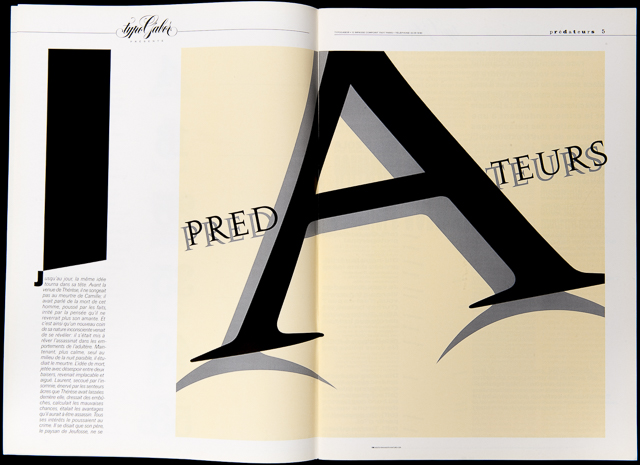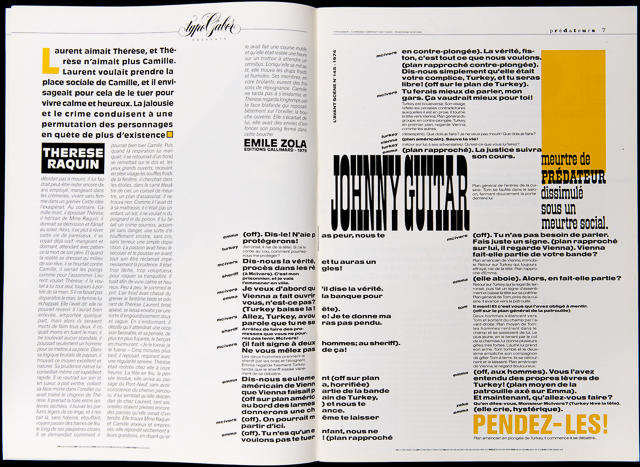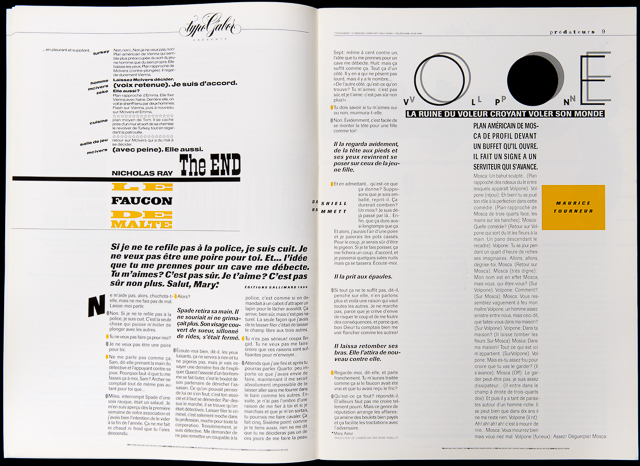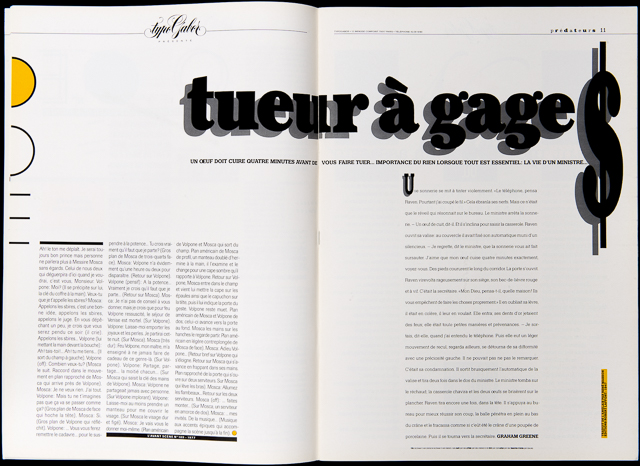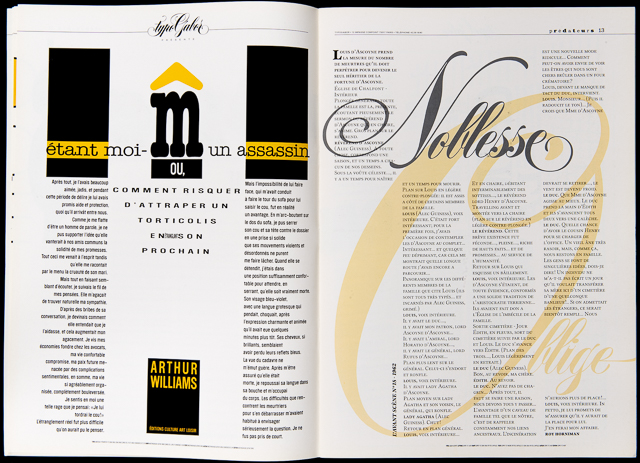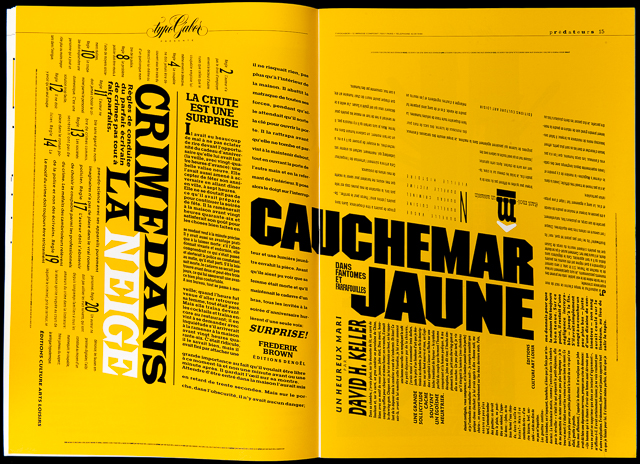
« TypoGabor présente » N°16 | Meutres
«Même si certaines manifestations graphiques sont en germe dès 1968, typoGabor est fondée en 1973 par Paul et Peter Gabor. L’activité de la société est double : atelier de création graphique autour des clients historiques de Paul Gabor et société de services typoGraphiques sous l’égide de Peter Gabor.
Les premières années de typoGabor sont rythmées par le fonctionnement coûteux et limité des Diatronic de Berthold. Tant et si bien qu’à la fin des années 1970, la continuité d’exploitation semble compromise. C’est à la faveur d’une annonce dans la revue CARACTÈRE que Peter Gabor découvre l’Alphatype. Il y voit l’amorce d’une révolution du digital. Ce sera son ami (depuis) Raymond Aubry, chef d’Atelier de Graphiservice à Bruxelles qui achèvera de le convaincre. Un système de composition américain venant de Chicago, qui pour la première fois, propose non plus d’acheter mais de louer (prix dérisoire) des polices de caractères, ce qui porte l’offre et la diversité typographiques à un niveau inédit : 1 000 polices contre 80 sur Diatronic auxquels s’ajoutent 16 polices supplémentaires tous les mois.
« typoGabor présente » naît en 1980 de deux constats. Il ne s’agit plus de faire de la Pub pour une entreprise, mais d’informer et d’éduquer un marché. La Publicité. Un marché où s’affrontaient une trentaine de concurrents proposant tous à peu près les mêmes services (24 / 24, coursiers, catalogues de calibrage gratuits et qualité de composition supérieure à celle de l’édition ou de la Presse). typoGabor connaît alors le succès. Les Directeurs Artistiques affluent et les commandes doublent de volume en l’espace de 2 an. Mais la formule marketing du magazine ne plaisait plus à Peter Gabor. Il y préféra une formule nouvelle autorisant toutes les expérimentations typographiques.
Le magazine littéraire de typoGabor était né. Plusieurs directeurs artistiques vont se succéder dans les cuisines typographiques de la maison Gabor. Bill Butt, Jérôme Binda, Philippe Duriez et pour finir Paul Gabor qui revient en 89 par une magistrale œuvre consacré aux Droits de l’Homme. L’Âge d’Homme.
L’expérience de la photocomposition fut de courte durée. Le Postscript arrive sous la forme commercialisée d’Adobe Type Manager et tous les prestataires de composition perdent 50 clients par jour à partir de 1990. Peter Gabor tenta encore d’adapter son entreprise en devenant le premier compositeur qui a basculé la totalité de son fonds sur Macintosh. Mais les dettes s’accumulant et victime d’un administrateur judiciaire peu scrupuleux, il finit par baisser les bras, non sans avoir personnellement créé 4 polices de caractères pour le Journal Libération en 1994.
Une aventure de vie passée à promouvoir la diversité et la qualité de composition, parce que comme l’aimait à rappeler son père Paul, d’après une phrase de Jean Cocteau : « Le style n’est pas une danse mais une démarche ».
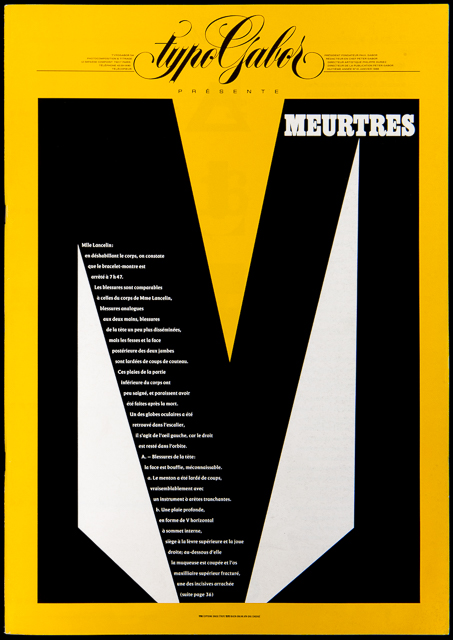
Affreux, le crime des Sœurs Papin. Elle ont commis l’impossible de l’horreur et pourtant… Il y a une explication à leur acte meurtrier. Le rapport ou plutôt le non-rapport à la réalité.
Tout se passe pour elles comme si l’imaginaire de leurs frustrations, leur désespérante quête d’une affection homosexuelle partagée, qui se mue en une machine déchiquetante et broyante, se superposaient à un monde schizophrénique qui n’est pas le leur.
Elles ont traversé un miroir où nous pourrons reconnaître au passage d’autres meurtres et d’autre crimes que l’histoire de la littérature a rendus célèbres. Nous avons cherché au détour de cette anthologie à reconnaître quelque catégorie de manifestation meurtrière. Le lieu géométrique commun pourrait-on dire de ce crime serait la stratégie… Stratégie du prédateur qui en veut uniquement à l’argent du voisin, stratégie des amants qui se déchirent de trop ou pas assez s’aimer, stratégie du Soi qui lutte en permanence avec l’image du père, et tel chez Kafka, n’arrive pas à décoller de l’univers autopunitif et concentrationnaire, où l’a entraîné un excès d’amour Œdipien.
Nous avons voulu débusquer les meurtres dans ce qu’ils ont de communs à l’humanité, leur rapport à un besoin existentiel : être plus ou ne plus être. Nous nous sommes essayés méthodiquement à classer, tels des entomologistes, les genres, les espèces, les filiations, et ce voyage qui n’est certes pas un tribunal, nous aura permis de découvrir tantôt des territoires communs au Comte Zaroff et au Marquis de Sade, tantôt les revanches de l’âme sur l’organisation réfléchie de l’indifférence sociale. Mais rassurez-vous : chasser le Meurtre ne nous a pas rendus meurtrier pour autant.
Tout au plus avons-nous égratigné la typographie au passage, croyant bien faire que d’assassiner des idées reçues ne pouvait conduire qu’à un résultat transitoire, mais bénéfique : le doute. L’assassin en herbe de ce journal n’est autre qu’un jeune diplômé de « Penninghen » rencontré au hasard d’un cours. Et nous rendons un vif hommage à sa créativité, à sa tactique pré-méditée (durant les heures où le monde sommeille) pour la parfaite maîtrise avec laquelle il a organisé l’espace criminel d’une humanité sollicitant un peu plus d’amour… De Soi.
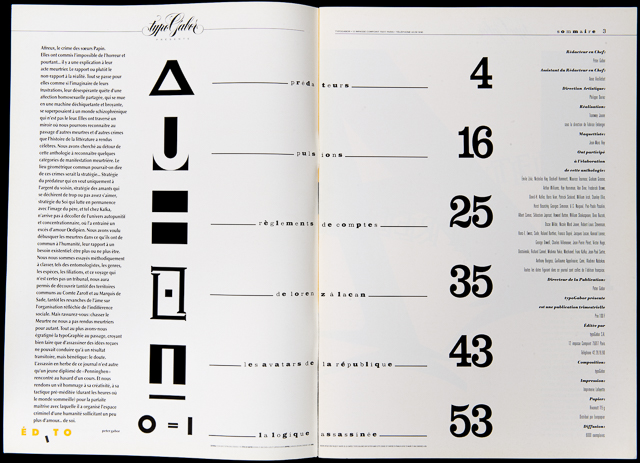
Meurtres : c’est sans doute un des magazines qui m’a donné le plus de fil à retordre. Allez savoir. Tout d’abord je me suis retrouvé sans Rédac. Chef.
Léon-Marc Lévy a pris du champ alors que le magazine Humeur d’Humour s’est terminé sur une queue de poisson. Nathalie Baylaucq étant partie à New-York avant d’avoir terminé la maquette j’en ai conçu moi-même la couverture. En essayant de respecter l’esprit de sa mise en page. Du coup tempête dans un verre d’eau. Patrick Amsellem se fâche avec moi et Léon-Marc, pris entre deux feux se retire pour ce numéro me laissant me «démerder» tout seul.
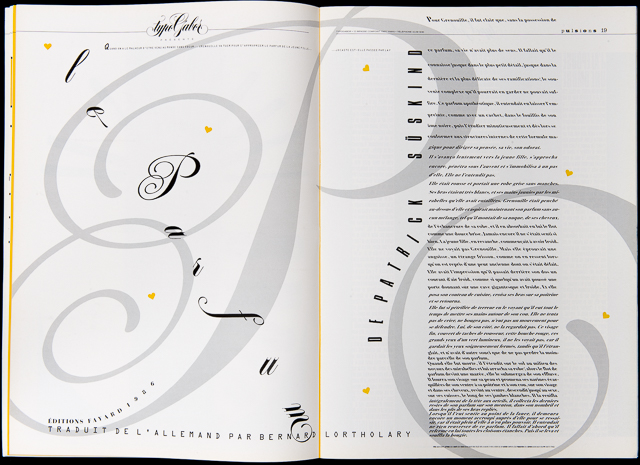
Et Philippe Duriez de décliner tout le vocabulaire graphique de Paul Rand, avec brio, élégance et maîtrise (presque) complète des principes de lisibilité.